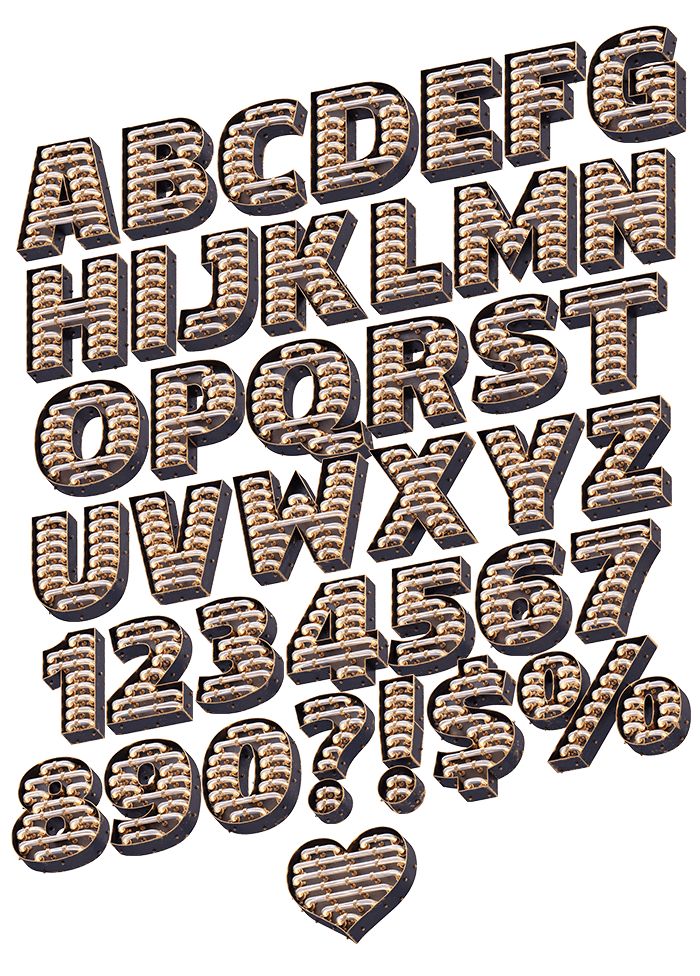
Стимпанк Шрифт Клипарт Картинки | Премиум-изображения в высоком разрешении
Nidus Nidus — один из тех шрифтов без засечек, которые делают дизайн чрезвычайно простым, даже если общая композиция перегружена. Вы можете использовать его, не беспокоясь о том, что финальная часть будет выглядеть слишком громко. В Nidus все сбалансировано и используются международные глифы, в том числе 160 букв.![]()